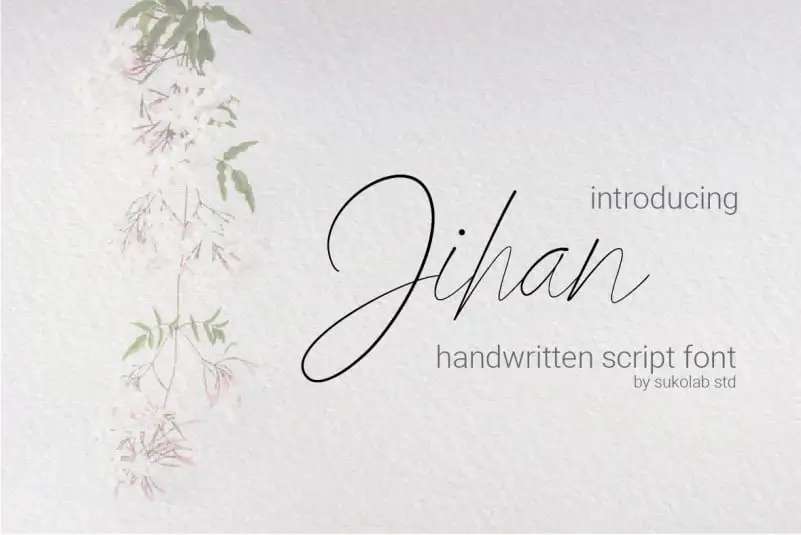
Jihan Script Font – Download Grátis
A Jihan Script Font é uma escolha perfeita para quem busca expressar elegância e universalidade em seus projetos digitais. Feito por Sukolab std., esta fonte script pode personalizar seu texto de maneiras incríveis. Com muitas características adicionais, essa font se destaca tanto para títulos quanto para textos mais longos. Perfeito para criações como nomes de marca, convites especiais, posters e capas de livros, a Jihan Script Font tem um estilo elegante que se assemelha à letra de uma pessoa escrevendo. Ela não apenas oferece uma variedade de opções para personalizar seu design, mas também permite que você dê vida ao texto através da sua própria interpretação artística. É uma escolha inteligente para qualquer projeto onde um ar elegante e único é desejado. Ao usar a Jihan Script Font, não apenas você estabelece um tom de estilo, como também pode criar um impacto visual significativo em suas criações digitais. Seja para projetos pessoais ou profissionais, a Jihan Script Font oferece uma maneira única e intrigante de expressar sua personalidade no mundo digital.